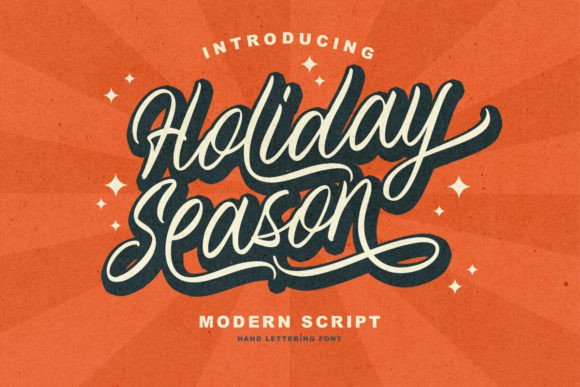
Holiday Season
適切なデザイン要素を見つけるのは難しい場合がありますが、Holiday Seasonは作品を即座に引き立てる優れたコレクションを提供します。
POD(オンデマンド印刷)製品、結婚式の招待状、またはソーシャルメディアのグラフィックを作成している場合でも、Holiday Seasonは理想的です。